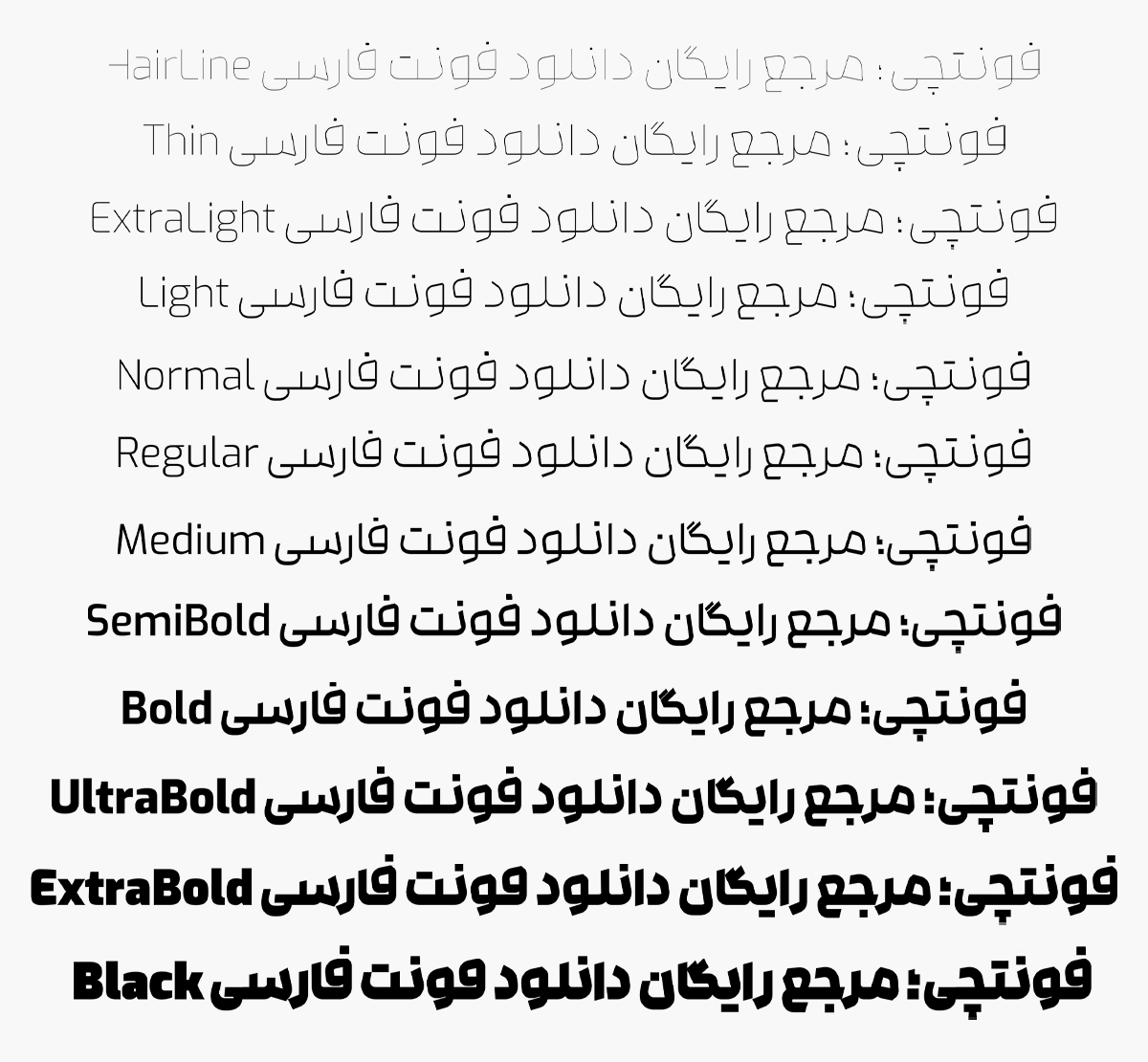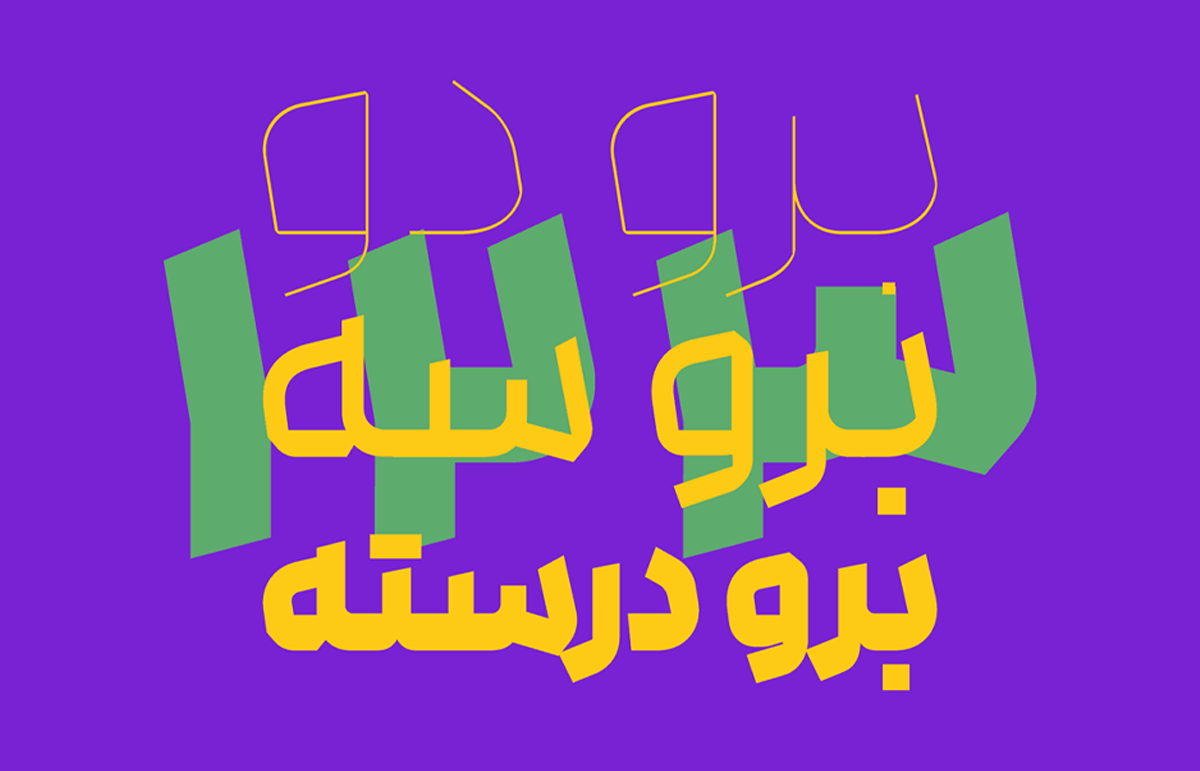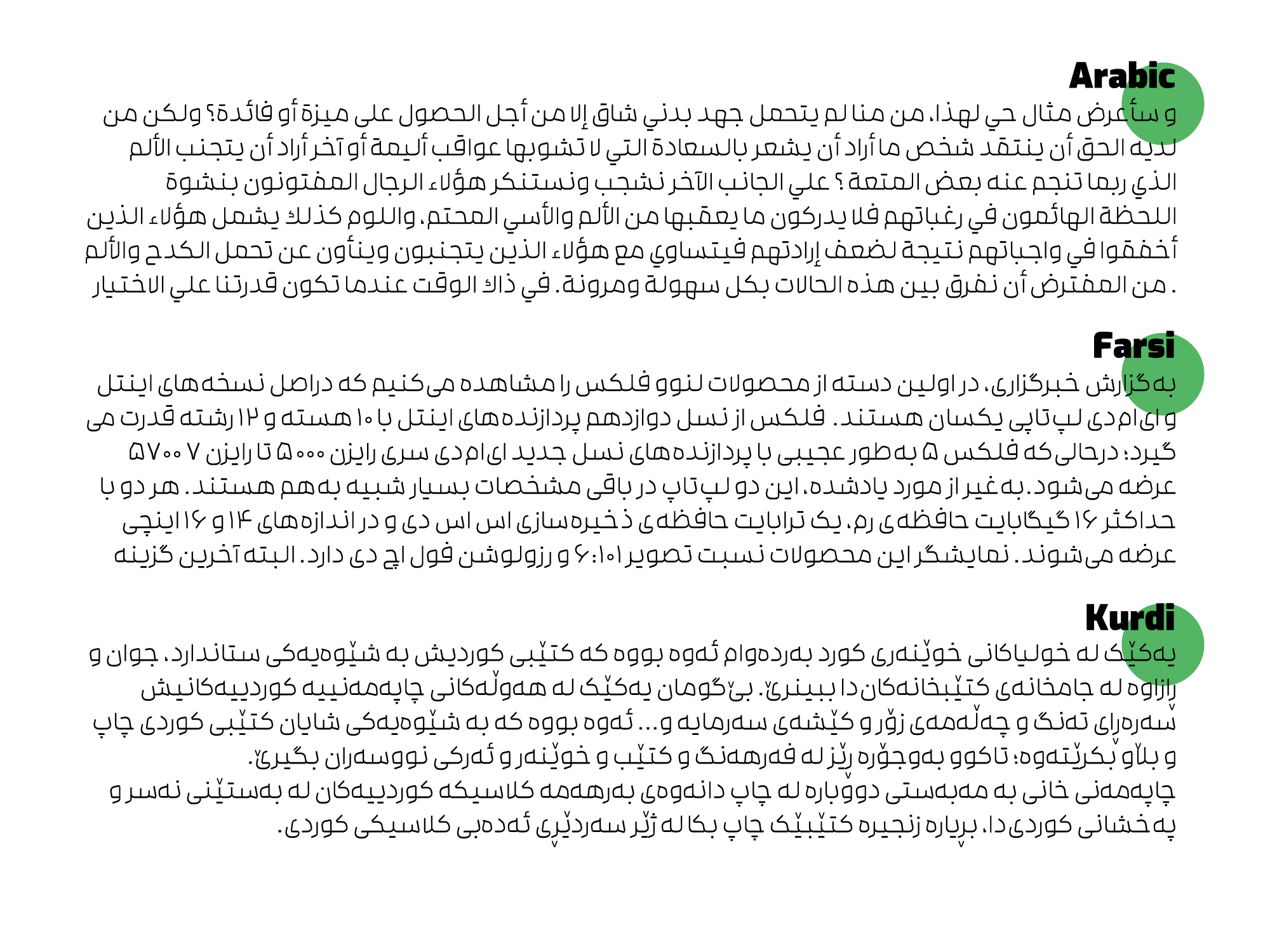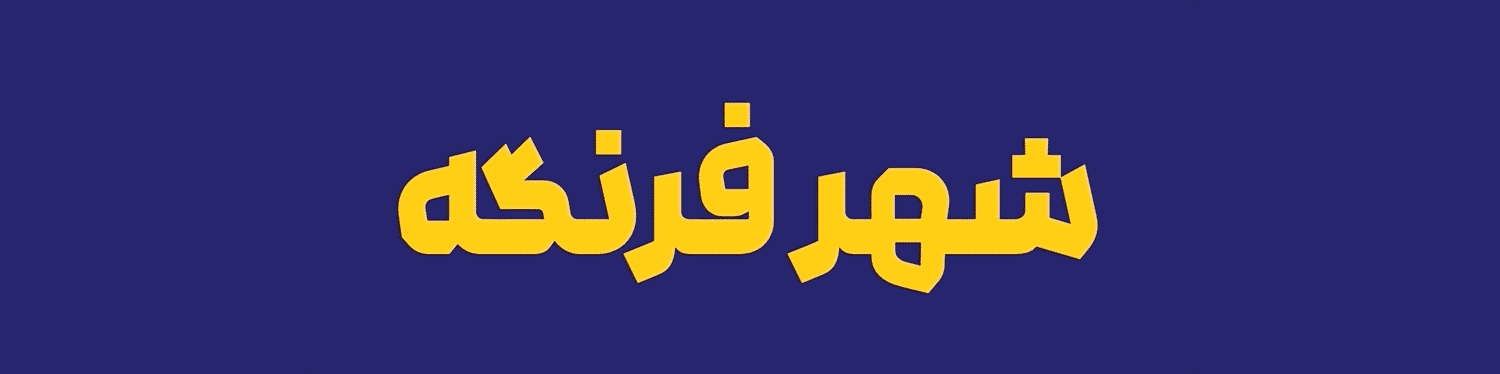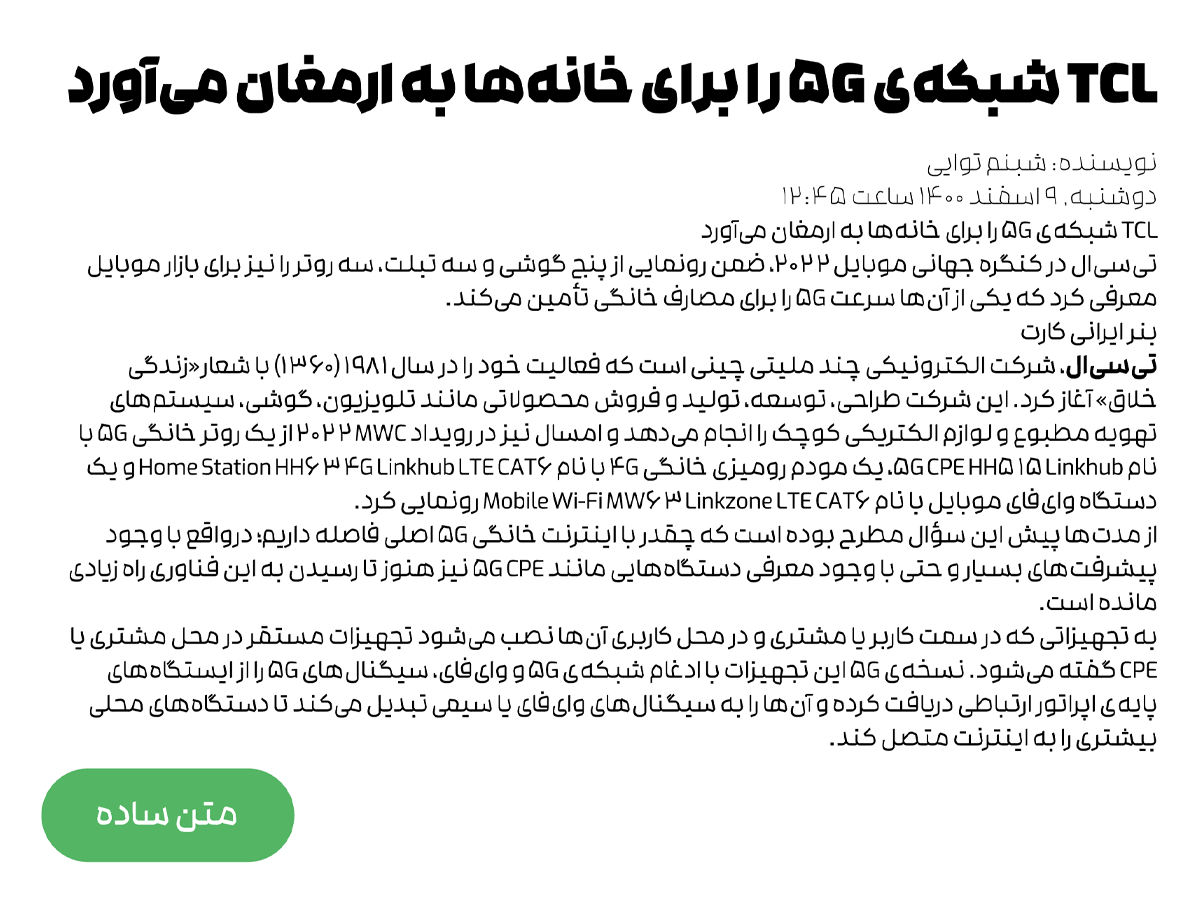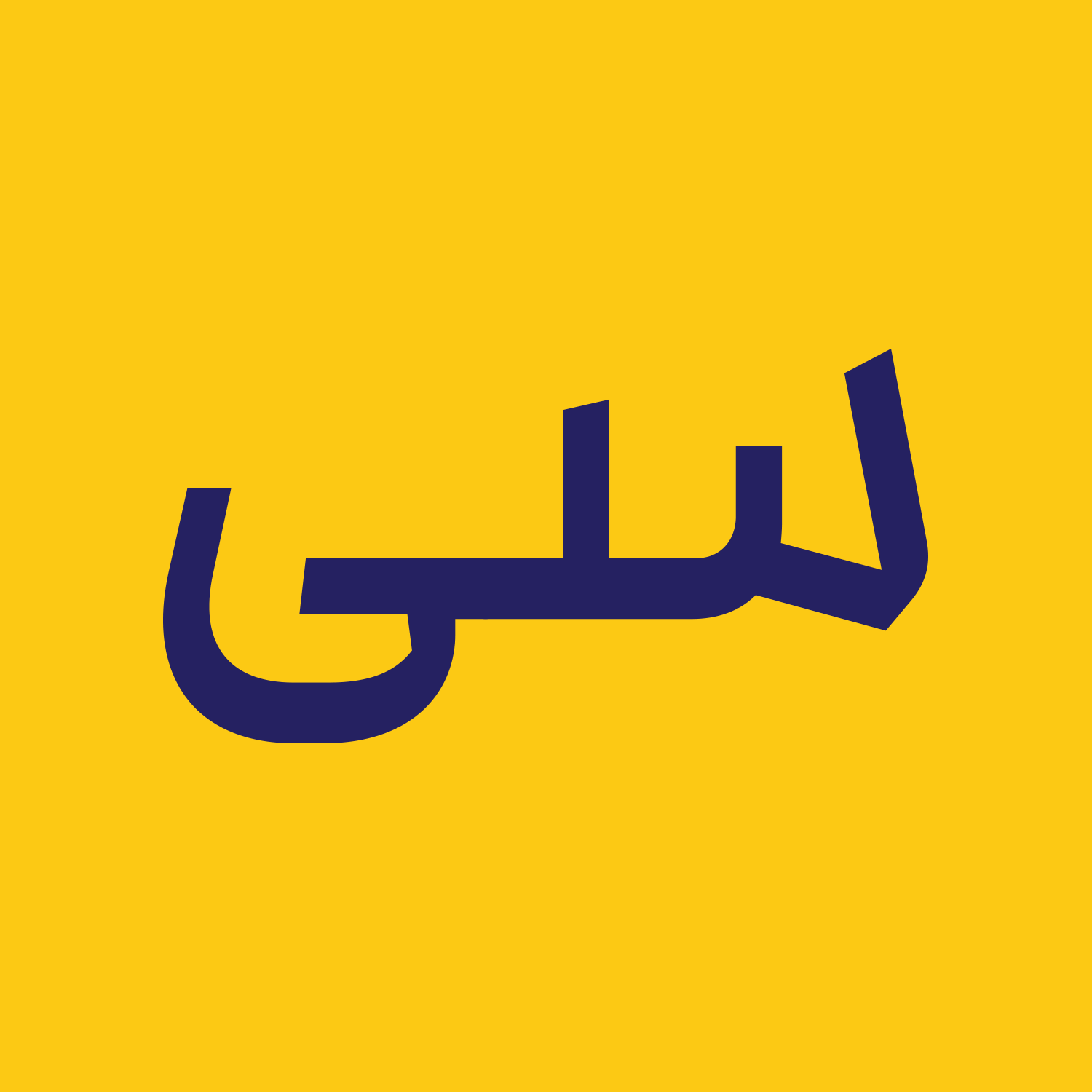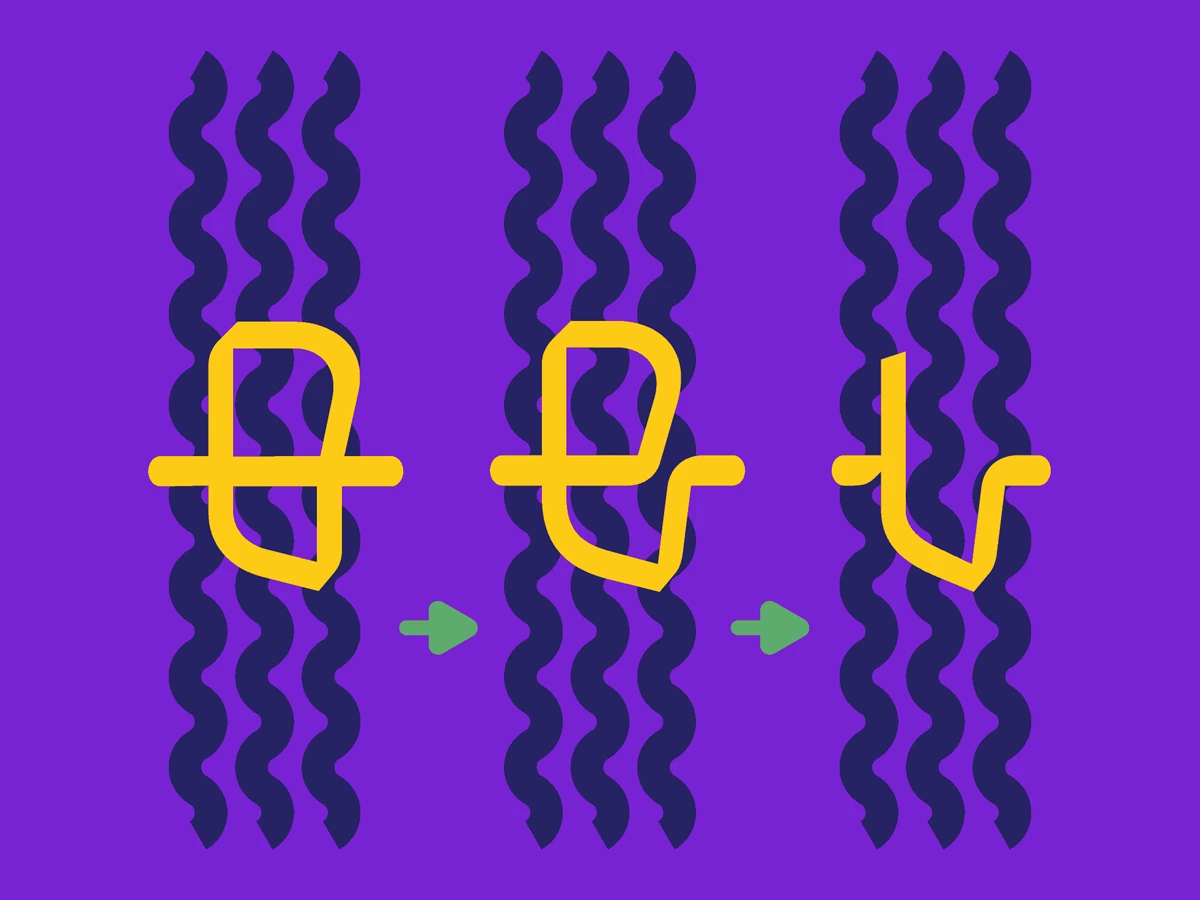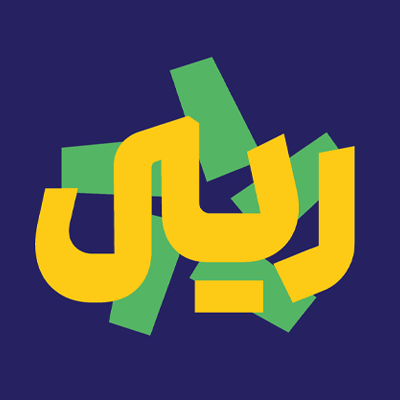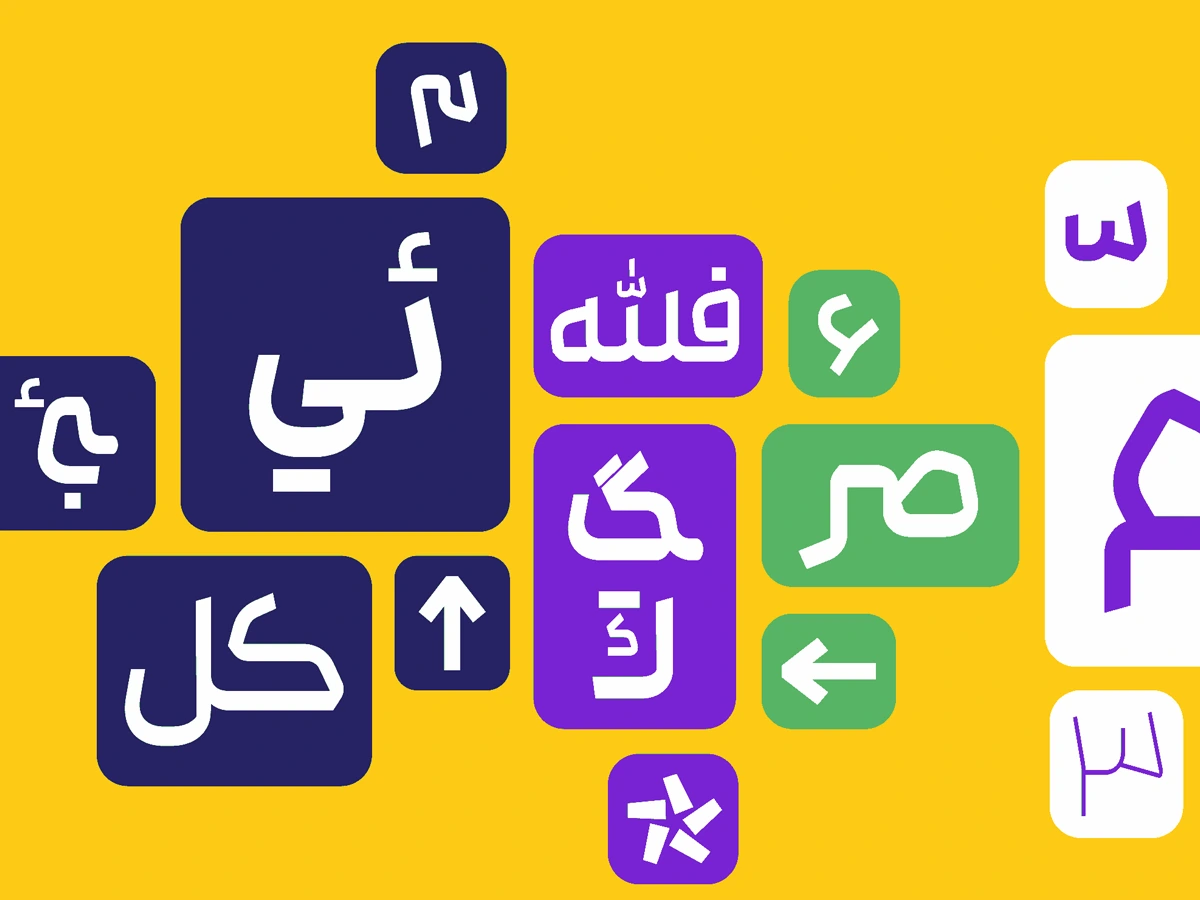
فونت رخ (Rokh)
فونت رخ (به انگلیسی: Rokh) قلمی در گروه هندسی و مناسب متن است که با پشتیبانی از نسخه وریبل و ۱۲ تنوع وزن بسیار نازک تا سیاه، میتواند برای فضاهای مختلفی مثل وب، تبلیغات و طراحی انواع تصاویر در پروژههای گرافیکی مناسب باشد. فونت رخ رایگان نیست و میتوانید این قلم را در سه بسته اقتصادی، نیمه حرفهای و حرفهای خریداری کنید که هر بسته بر اساس تعداد وزن و نسخه وریبل متغیر هستند.
اگر قرار باشد در سایر فونت های فارسی بهدنبال فونت نزدیک به این قلم باشیم، شاید بتوان گفت که فونت Rokh ترکیبی از دو فونت داراب و فونت مدام باشد؛ از این جهت که سبک فونت مدام را برای گردی و دندانه حروف و شکل قائم فونت داراب را هم برای خطوط، با این تفاوت که فشردهتر است در خود دارد.
در ادامه این مطلب از سایت فونتچی؛ به نقد و بررسی قلم رخ خواهیم پرداخت. فونتی که برای انواع متنهای کوتاه و بلند مناسب بوده و جدای از این میتوان از آن به عنوان یک فونت لوگوتایپ (فونت مناسب طراحی لوگو) استفاده کرد. این فونت توسط کامیاب جعفری طراحی شده است.
بررسی و دانلود فونت رخ (Rokh)
با وجود اینکه فونت Rokh هندسی است، اما با خاصیت نمایشی و کنتراست بالایی که دارد، برای استفاده در متنهای طولانی و وزنهای مختلف کاملا عالی عمل کرده است. در این فونت چشمها و دندانهها در مقایسه با خطوط قائم دارای ارتاع نسبی بالاتری هستند و در کنار الفهای کوتاه قرار گرفتهاند.
چنین ویژگی باعث شده که کنتراست فونت در کرسی بالایی کمتر باشد و بیشتر توجه را معطوف به کرسی پایین کند. همچنین ساختاری فشردهتر را به قلم خواهد داد که از این جهت میتواند برای طراحی لوگو تایپ مناسب شود.
سبک طراحی و وزن فونت رخ
در طراحی فونت رخ تمام تلاش بر این بوده که فرم حروف درای شخصیت منحصر به فرد خود باشد که این باعث میشود به راحتی از دیگر فونتهای هندسی قابل تشخیص باشد. در وزنهای سنگین هم بهطور کاملا عمدی حروف «ر، ز، ژ» با حرف نون در تعاملی بسیار نزدیک هستند که موجب نمایشیتر شدن فونت شده است.
پشتیبانی از ۵ زبان متنوع
فونت رایگان رخ، به پشتوانه تاریخچه عمیقی که از زبان فارسی دارد، از سایر زبانهای بر پایه خط رسم فارسی مثل عربی، کردی و اردو هم پشتیبانی میکند.
حروفی که در این زبانها با رسمخط فارسی یکسان باشند دارای گلیف مشترک بوده و در عوض حروفی که ظاهری متفاوت نسبت به زبان فارسی دارند، از گلیف اختصاصی خود بر اساس کد یونیکد برخوردار هستند که با تنظیم صفحه کلید روی زبان مورد نظر تایپ خواهد شد. یا اینکه میتوانید با دانلود فونت رخ برای فتوشاپ با استفاده از تنظیمات اپنتایپ به هر گلیف دسترسی داشته باشید.
در تمامی زبانهای این فونت کلیه حروف و اعراب متناسب با زبان مورد نظر طراحی شده است تا برای استفاده در همان زبان مناسب باشد. اگر از فونت عربی رخ استفاده میکنید، اعراب و اعداد در همان سبک زبان طراحی شدهاند. حروفی همچون «ک، ی، ه، ؤ، ئ» در زبان عربی، یا حروف «ی» پایانی و «ـه، ـهـ» در زبان اردو که شکل متفاوتی از زبان فارسی دارند در این قلم بهخوبی رعایت شدهاند تا اصالت هر زبان را حفظ کنند.
در فونت انگلیسی رخ نیز همین قواعد ضمن اینکه حروف لاتین نیز بر اساس همان سبک طراحی برای زبان فارسی در نظر گرفته شده، به خوبی رعایت گردیده است.
وریبل فونت رخ با قابلیت تغییر وزن
قابلیت دیگر این فونت خانوادهدار پشتیبانی از نسخه متغیر است که با نام rokh font variable شناخته میشود. زمانی که از فونت وریبل رخ استفاده کنید، چه در محیط نرمافزاری سیستم عامل و چه برای سایت، لزومی به استفاده از چند فایل فونت برای وزنهای مختلف ندارید. بلکه تمامی وزنهای ۱۲ گانه در قالب یک فایل فونت در دسترس هستند که اتفاقا حجمی کمتر از ۲ وزن را دارد.
قلم متغیر رخ امکان تغییر وزن حروف را از وزن بسیار نازک HairLine گرفته تا وزن ضخیم آن، Black در خورد دارد. جدای از این ویژگیهای دیگر این قلم همچون پشتیبانی از گلیفهای ریال، حروف و ترکیبات جایگزین، اعداد فارسی و عربی نیز در همین نسخه وجود دارد.
سبک نقطه گذاری در فونت رخ پیوسته است و انتظار میرود در آپدیتهای بعدی، خصوصا با پشتیبانی که از نسخه وریبل دارد شاهد دسترسی به سبک نقطهگذاری متنوع هم باشیم.
اعداد فارسی هک شده و بدون حروف انگلیسی
ضمن پشتیبانی کامل این فونت از اعداد فارسی و عربی، در بسته دانلود فونت رخ یک نسخه مخصوص اعداد هک شده قرار دارد. این نسخه از فونت به این صورت هستند که به جای درج گلیفهای اعداد لاتین، از اعداد فارسی استفاده شده است.
در نتیجه حتی زمانی که صفحه کلید شما فارسی باشد یا اینکه اعداد لاتین را از از کلیپبورد درج کنید، در هر حالتی اعداد فارسی نمایش داده میشوند. چرا که اعداد به صورت هک شده در این نسخه قرار دارند. این گروه از فایلهای فونت در پوشه Farsi Digits به صورت مخفف با FD نامگذاری شدهاند.